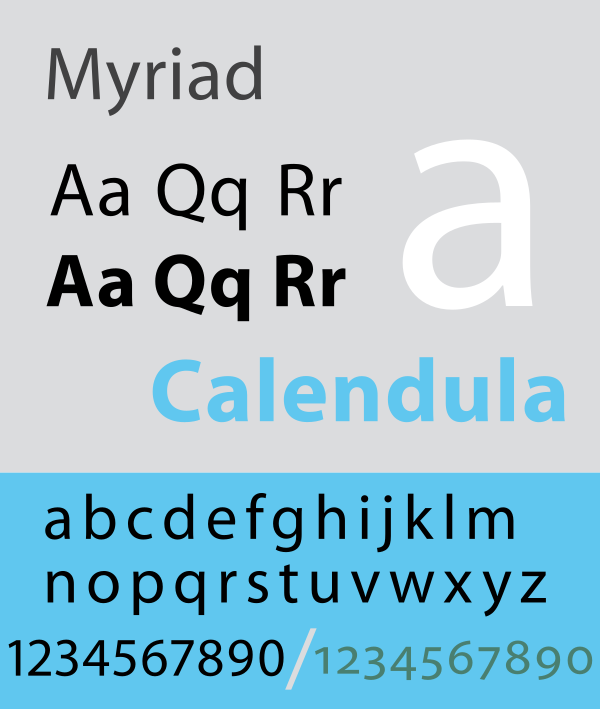
Myriad (шрифт)
Myriad — семейство шрифтов класса гуманистический гротеск, разработанное Робертом Слимбахом и Кэрол Туомбли для Adobe Systems.
Данный шрифт используется компанией Apple в выпускаемых устройствах.
| Myriad | |
|---|---|
| Стиль | Гротеск |
| Классификация | Гуманистический гротеск |
| Дата создания | 1992 |
| Дизайнер |
Роберт Слимбах Кэрол Туомбли |
| Словолитня | Adobe Type[d] |
| Использование | Adobe Type |